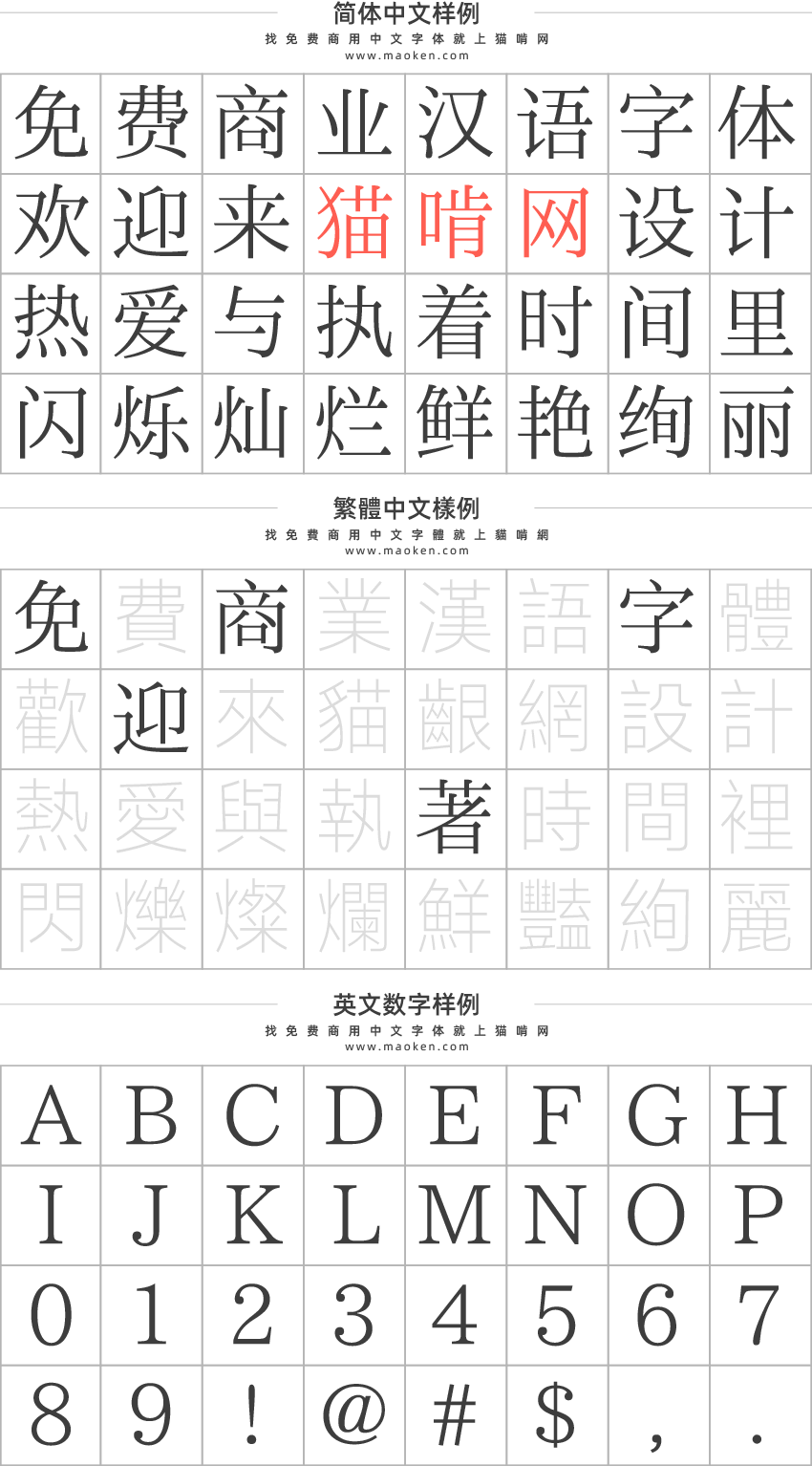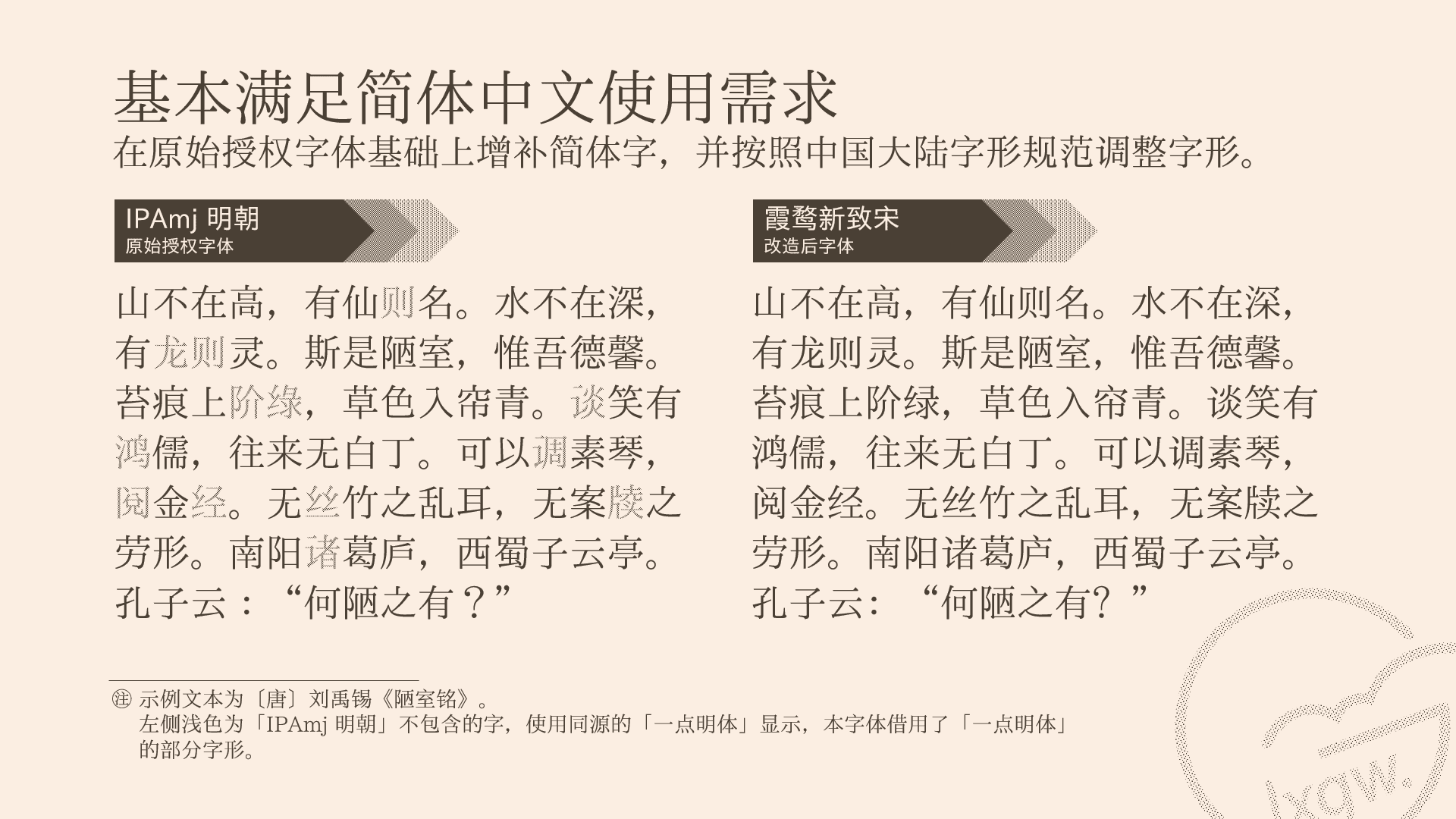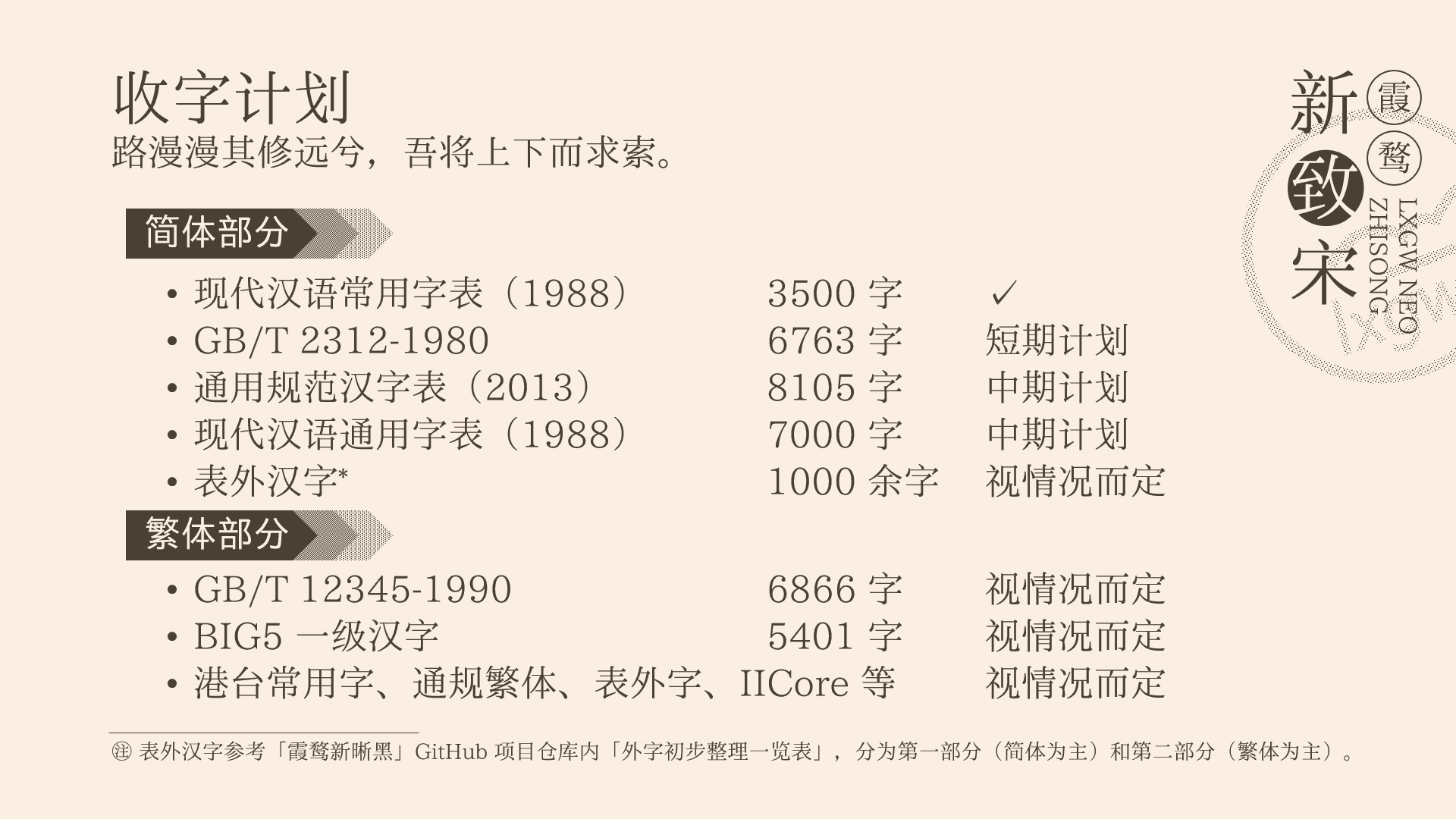
霞鹜新致宋:一款简约典雅的中文宋体字型,基于“IPAmj明朝”衍生
这是一款基于 IPAmj明朝 的中文开源字体,是将日本写法的字体改造成中国大陆规范写法的尝试。
本字体是「霞鹜新晰黑」的姊妹字体,尝试在「IPAmj明朝」原有字形的基础上,将其改造成中国大陆规范字形。
地不问东西,凡木刻的图版,向来是画管画,刻管刻,印管印的。中国用得最早,而照例也久经衰退;清光绪中,英人傅兰雅氏编印《格致汇编》,插图就已非中国刻工所能刻,精细的必需由英国运了图版来。那就是所谓「木口木刻」,也即「复制木刻」,和用在编给印度人读的英文书,后来也就移给中国人读的英文书上的插画,是同类的。
地不問東西,凡木刻的圖版,向來是畫管畫,刻管刻,印管印的。中國用得最早,而照例也久經衰退;清光緒中,英人傅蘭雅氏編印《格致彙編》,插圖就已非中國刻工所能刻,精細的必需由英國運了圖版來。那就是所謂「木口木刻」,也即「複製木刻」,和用在編給印度人讀的英文書,後來也就移給中國人讀的英文書上的插畫,是同類的。